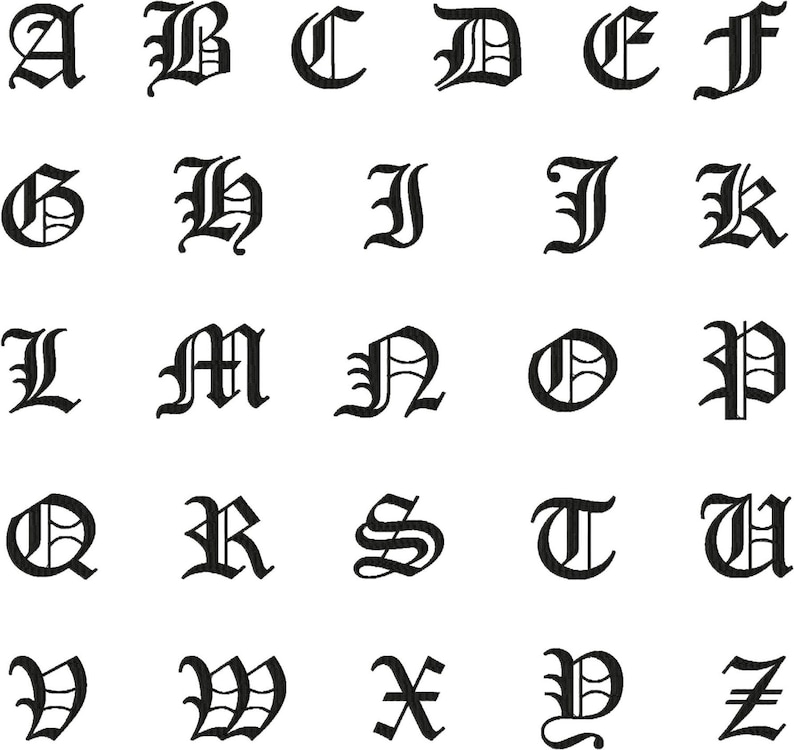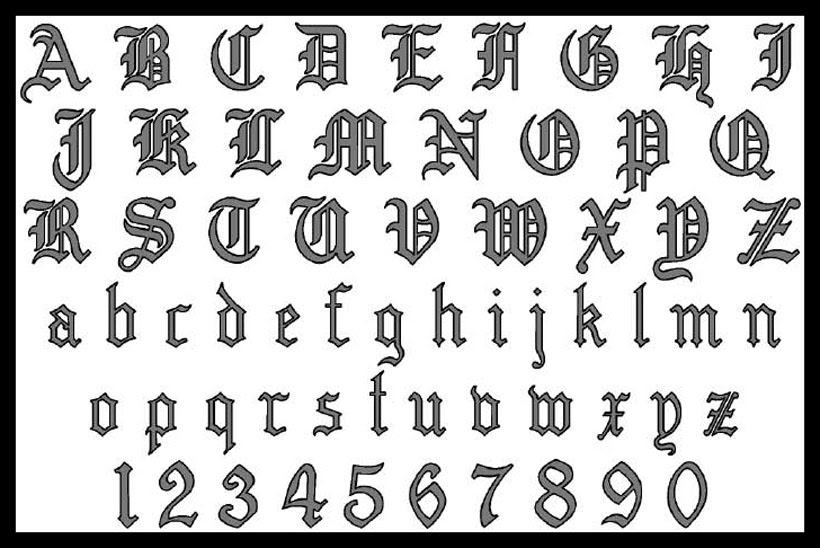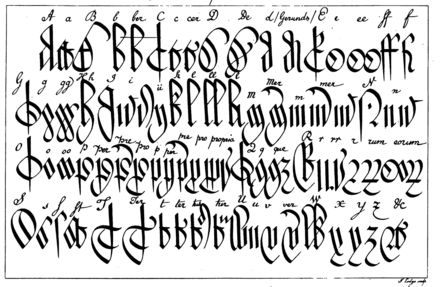
Старинный шрифт (старая антиква)По той причине, что печатные станки печатали только книгу, первые шрифты читались невероятно легко, т.
Старинные шрифты выглядят приятно и изящно, являются самыми лучшими для создания читабельного текста большого объёма. Старинные классические шрифты — одни из наиболее «незаметных», т.е. форма не мешает восприятию, обычно в них нет украшательства, которое раздражает глаз.
Современные шрифты (Переходная и новая антиква)
Современные шрифты придают особое значение структуре и форме, в которых исчезают последние следы шрифта рукописного происхождения.
Шрифты этого типа обладают блеском и элегантностью, но в то же время они имеют суровый и холодный внешний вид.
Они не очень читабельны, т.е. это не самый лучший вариант для объёмных текстов, т.к. резкий контраст толстое/тонкое создаёт эффект, называемый «ослепление», что усложнает восприятие.
У современных шрифтов есть засечки, но засечки на всех буквах горизонтальные и очень тонкие, с небольшими закруглениями или без них (в том месте, где соединяются засечки и шрих, нет скругления). Штрихи, создающие форму буквы, резко меняются от толстого к тонкому. Stress отсутствует.
Шрифты с плоскими засечками (slab serif)
Одним из результатов индустриальной революции стало появление рекламы. Сначала дизайнеры шрифтов пытались увеличить толстые штрихи букв современного шрифта, однако из-за чрезвычайно резкого сочетания очень жирных штрихов с очень тонкими текст было практически невозможно читать. Поэтому они сделали толще форму буквы.
У шрифта slab serif тоже есть засечки, они горизонтальные, но толстые. Жирные. Плиты. Штрихи, которые создают форму буквы, едва заметно переходят из толстых в тонкие.
Эти шрифты ещё называют егиетскими. Кроме того, эти шрифты ещё часто называют Clarendon, потому что Clarendon — самый лучший пример этой категории.
Шрифты без засечек (sans serif)
Под девизом Баухаус «Форма следует за функцией» шрифты были сведены к самой простой и фукциональной форме — гарнитуре Futura. Эта школа оказала большое влияние на дизайнерские представления всего мира.
У шрифта sans serif нет засечек. Помимо этого, штрихи, создающие форму буквы, имеют почти незаметный переход от толстого к тонкому (существует лишь несколько исключений, например шрифт Optima). Sans serif стремится к очень большой высоте-х и хорошо смотрится на странице.
«Расхлябанные» шрифты (fringe type)
Шрифты frige — расхлябанные (которые называют также grunge, garage, deconstructive, edge, lawless или просто ugly) в основном переконешнные, шизофренические, нарочно изуродованные и трудные для чтения.
Но, без сомнения, их легко идентифицировать и отличиь от любых других шрифтов в истории. И многие из них красивы в своём уродстве. И их невероятно весело использовать.
Рукописные шрифты (scripts)
Рукописные и декоративные шрифты появляются неожиданно в каждом периоде истории типографики. Рукописные шрифты, конечно же, существую самых различных видов: старопечатные (как во многих Библиях, переписанных от руки переписчиками), каллиграфические (как в свадебных приглашениях), чертёжные (как на рисунках архитекторов), мультипликационные и т.д. Никто особенно не заботится об идентификации шрифтов этой категории.
Декоративные шрифты
Декоративные шрифты также примечательны — они сделаны из балетных тапочек, или верёвки, или японских пагод, или пыли от стирательной резинки. Декоративные шрифты не предназначаются ни для чего иного, кроме деокрации. Они могут добавить энергию в публикацию, создать определённый образ или подчеркнуть содержание. Если слишком часто их использовать, они могут разрушить дизайн.